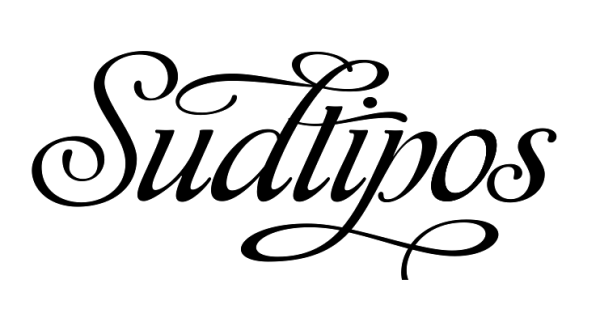
• Land: Argentinien
• Ort: Buenos Aires, Argentinien
Sudtipos ist ein in Argentinien ansässiger Schrifthersteller, der von Ale Paul, Ariel Garofalo, Claudio Pousada und Diego Giaccone gegründet wurde.
Die Foundry ist insbesondere für ihre expressiven und umfangreich ausgebauten Schreibschriften bekannt.